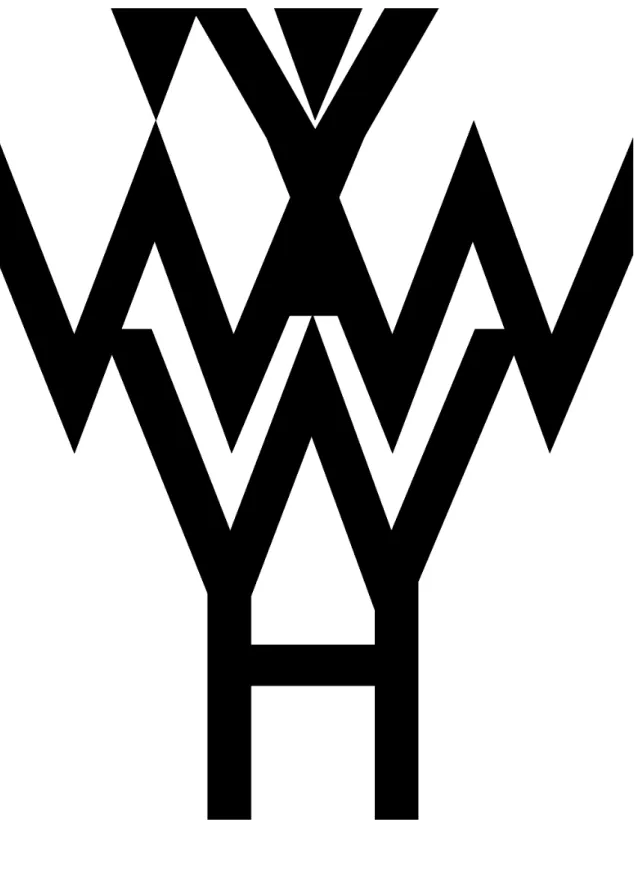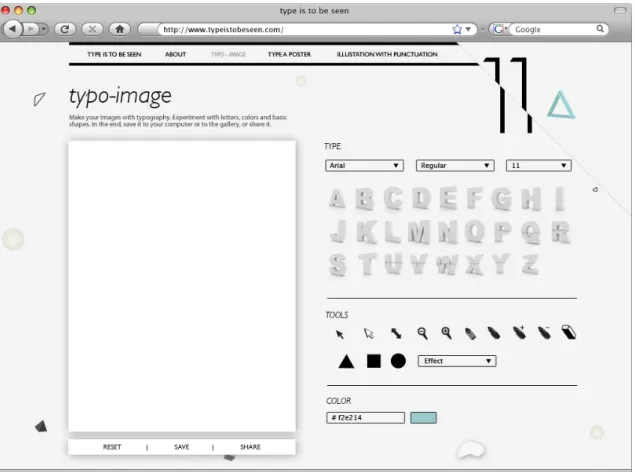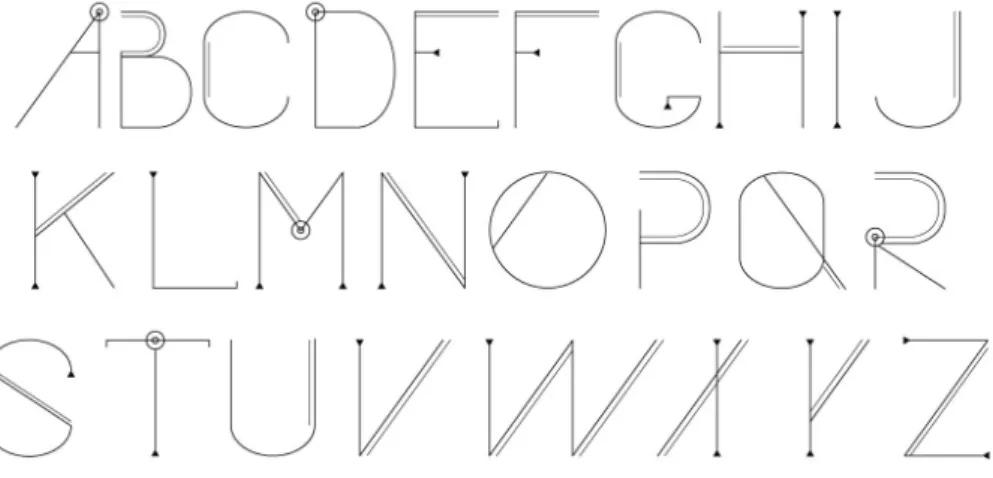
A tipografia como forma de expressão autónoma
A T
IPOGRAFIA
C
OMO
F
ORMA DE
E
XPRESSÃO
A
UTÓNOMA
[TRABALHO DE PROJECTO / A TIPOGRAFIA COMO FORMA DE EXPRESSÃO AUTÓNOMA]
Type is to be seen é uma plataforma ligada à rede que pretende fazer
com que as pessoas, de uma forma geral, e os seus utilizadores, em particular, reflictam sobre as letras enquanto forma de expressão gráfica e não apenas como peças que em conjunto formam palavras. As letras são o menor elemento da tipografia, um conjunto de letras irá formar uma fonte, e os vários comportamentos de uma fonte constituirão um tipo de letra. Enquanto tema central do projecto, interessa-me estudar a tipografia, não tanto pelo lado do desenho de letras e seus pormenores técnicos, mas antes como forma (ou imagem), numa tentativa de diminuir o receio que existe no meio do design em relação a convencionalismos e tradições, nomeadamente no que diz respeito à funcionalidade e invisibilidade do design e legibilidade da tipografia, que por vezes não permitem que os trabalhos atinjam o seu máximo potencial expressivo.
O projecto ganhou amplamente o título de “A tipografia como forma de expressão autónoma” devido à importância da componente teórica, onde se faz a contextualização da parte prática. Este site nunca poderia fazer sentido sem falarmos antes do modernismo e do advento dos meios digitais. Sendo assim, o primeiro capítulo corresponde ao estudo do pico do modernismo e aos "ismos" da sua arte. Eles constituíram uma das épocas mais marcantes e revolucionárias na arte e serviram para alterar a forma como as pessoas olhavam para os tipos de letra. Antes disto, a tipografia estava apenas ligada à imprensa mas, a partir das décadas de 1910/ 1920, as letras começaram a mover-se livremente nas páginas pela primeira vez. Foi adoptada uma atitude nova que iria marcar de forma profunda as décadas seguintes.
O segundo capítulo concentra-se no advento do computador e da internet e no nascimento daquilo que pode ser chamado de era digital, tendo início na década de 1980. Com o aparecimento dos meios digitais e a invenção do Postscript, que veio tornar possível trabalhar a tipografia dentro dos computadores, a possibilidade de criar tipos de letras chegou progressivamente às mãos de todos os utilizadores. Por esta altura, o design gráfico tomava novos contornos e ganhava um destino mais amplo e um papel cada vez mais importante na sociedade. Vários foram os designers que contribuíram para uma espécie de anarquia organizada dentro da tipografia, que elevou o seu potencial expressivo ao mais alto nível.
No terceiro capítulo é explicada a componente prática: o site propriamente dito. Aqui são descritas as várias actividades que o utilizador poderá realizar no site, apenas com recurso a letras, cor e formas geométricas básicas, numa experiência interactiva.
[PROJECT / TYPOGRAPHY AS AN AUTONOMOUS FORM OF EXPRESSION]
Type is to be seen is an online platform connected to the web that intends to make people in general and its user in particular reflect on letters as graphic expression forms and not just as pieces that set together make up words. The letters are the smallest element in typography, a set of letter will make a font and the several behaviours of a font will make a typeface. Here typography matters as a central theme, not typography as the drawing of letters and its technical details, but typography as a form (or image), in an attend to remove part of the fear that exists in design because of conventionalisms and traditions, naming in what concerns the functionality and invisibility of design and legibility in typography, that sometimes doesn’t allow works to achieve their maximum expressive potential.
This project gained the wider title of “Typography as an autonomous form of expression”, due to the importance of the theoretical component that contextualizes the practical part. This website would never make sense if we didn’t speak previously of modernism or the advent of digital media. Therefore, the project is divided into three parts: two theoretical parts and one practical part. The first part correspond to the study of the peak of modernism and the “isms” of its art that are one of the most striking and revolutionary to change the way people with look at typefaces. Before all of this, typography was connected to the press but ever since the 1910s and 1920s, the letters started moving freely through the pages for the first time ever. A new attitude was adopted that would leave profound marks on the decades to come.
In the second chapter, that refers to the 1980s and the advent of computers and the internet one witnesses the birth of what can be called the digital age. With the digital media and the invention of Postscript, that made possible to work with type inside the computers, it was made possible for everyone to create their own typefaces. By this time, graphic design had gotten new shapes and was gaining a broader destiny and a more important role within the society. Several were the designers that gave their contribution for a kind of organized anarchy within typography, that rose the expressive potential to its highest level.
Tipografia deveria ser um reflexo do seu tempo, cada época deve determinar um aspecto visual específico seu consequente. A assimetria é outro aspecto indispensável, que o autor considerava como a “expressão rítmica do design funcional” (Tschichold 1928, 68). A tecnologia é apenas um meio para atingir um determinado fim, e não o contrário. Estes autores apoiaram os fortes contrastes, pequenos/ grande, claro/escuro, horizontal/ vertical, etc., para criar unidade entre os vários elementos, de modo a organizar o texto de forma lógica, permitindo que o olho vá saltando de uma parte para a outra sucessivamente. A importância da forma, que não é independente, mas nasce de um propósito, dos materiais usados e de como estes são usados e a simplicidade geométrica. O branco do fundo tem igual importância formal por comparação aos outros elementos e deve ser usado deliberadamente para enfatizar ou diminuir o efeito do todo; e o branco é uma cor deveras importante neste movimento. Na Nova Tipografia a cor é utilizada de forma funcional e não metafórica, consoante o efeito visual, devendo dessa forma ser preferidos o branco, vermelho, amarelo, azul ou preto, no estado puro.